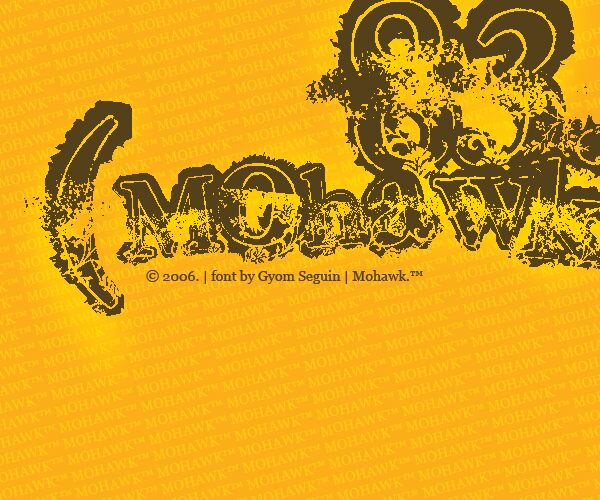
Mohawk to darmowy krój typu display o erodowanej fakturze, którego sylwetka sprawia wrażenie poszarpanej i wyblakłej. Dzięki nierównym górnym krawędziom i szerokim szeryfowym formom, które rozpadają się pod wpływem mocnego zniszczenia, litery wyglądają jak zniszczony nadruk lub wyżłobiony napis, a nie jak gładki font dekoracyjny.
Ta tekstura nadaje krótkim nagłówkom surowy charakter, idealny na ulotki zespołów, plakaty horrorów, nagłówki gier, grafiki na Halloween czy opakowania z efektem starzenia. Mohawk świetnie sprawdzi się na okładkach albumów lub w materiałach promocyjnych, gdzie poszarpana powierzchnia robi całą robotę, dzięki czemu nie musisz nakładać dodatkowych efektów grunge, aby uzyskać ten porysowany, uszkodzony wygląd.